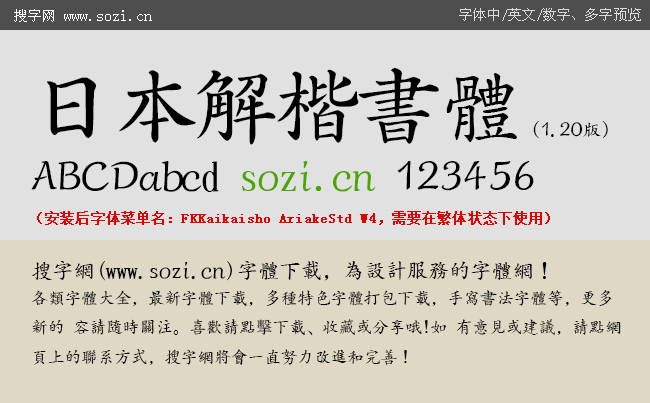
日本解楷書體
搜字網(wǎng)提供一款日本解楷書體日系中文字體下載,日本解楷書體是一款非常漂亮的楷書字體,字體粗細(xì)適中,看著讓人覺(jué)得非常的清新自然,可廣泛使用,適合應(yīng)用于廣告設(shè)計(jì)、名片設(shè)計(jì)、包裝印刷、產(chǎn)品設(shè)計(jì)等應(yīng)用。